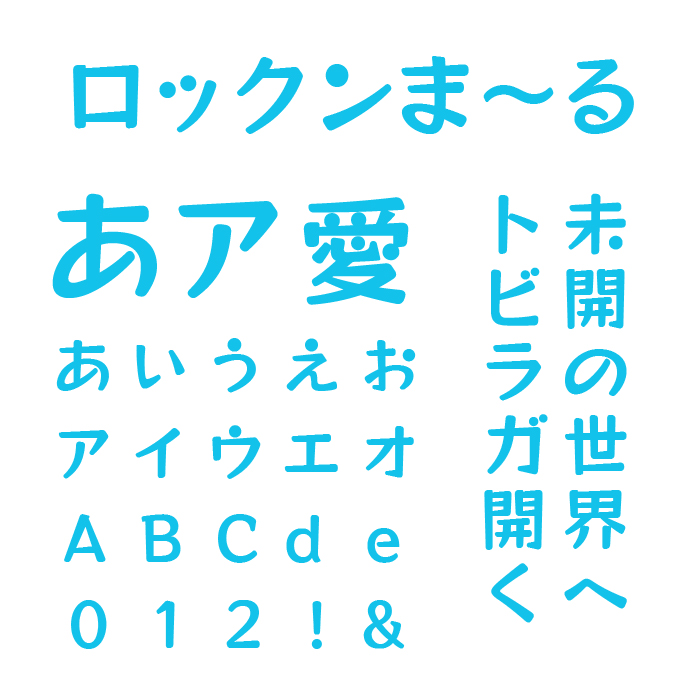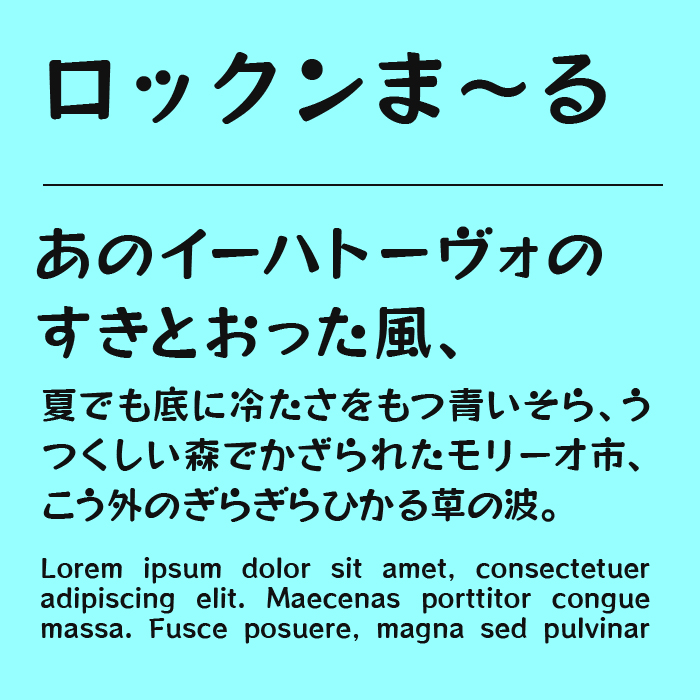
ロックンま〜るフォントは、ロックンロールone(RocknRoll One)フォントをベースに、角を丸めて太めの線に丸みを持たせた、元気で弾むような印象のデザイン系フォントです。
ひらがなが特に楽しげで、リズム感のある動きを感じさせます。並べるだけで音楽やリズムを思わせるようなデザインになります。
親しみやすい丸みがあるので、子供向けをテーマとしたデザインやほかにも、スナック菓子やポップな飲料のパッケージなど、楽しい雰囲気を演出したい場面にも向いています。
収録文字は、漢字・ひらがな・カタカナ・アルファベット・数字・記号が収録。